Một bài đăng tuyển dụng không chỉ thông báo công ty đang cần người. Nó còn là lần đầu ứng viên cảm nhận văn hóa, mức độ chuyên nghiệp và năng lượng của doanh nghiệp. Vì vậy, font chữ tuyển dụng, HR branding cần rõ ràng như một thông báo nhân sự, nhưng cũng phải có cá tính đủ để ứng viên nhớ đến thương hiệu.
Trong cùng một chiến dịch tuyển dụng, font có thể xuất hiện ở rất nhiều điểm chạm: poster job opening, banner LinkedIn, bài đăng Facebook, story Instagram, cover career page, email mời phỏng vấn, slide onboarding, handbook, bảng nội quy và ảnh recap hoạt động nội bộ. Nếu chọn font thiếu ổn định, toàn bộ hình ảnh HR sẽ rời rạc. Nếu chọn font đúng, thương hiệu tuyển dụng nhìn chuyên nghiệp hơn ngay cả khi nội dung rất ngắn.
Bài viết này gợi ý các font Việt hóa trên Font S99 phù hợp cho tuyển dụng văn phòng, startup, công nghệ, sáng tạo, bán lẻ, dịch vụ, agency, giáo dục và employer branding nội bộ. Mỗi font được trình bày riêng một dòng với anchor Tải về để bạn có thể tải xuống và thử trực tiếp vào thiết kế.
Ứng viên thường nhìn bài tuyển dụng rất nhanh. Họ cần biết vị trí gì, làm ở đâu, lương hoặc quyền lợi ra sao, hình thức làm việc thế nào và cách ứng tuyển có đơn giản không. Nếu font khó đọc, quá trang trí hoặc thiếu phân cấp, thông tin quan trọng sẽ bị chìm giữa ảnh nền, icon và màu thương hiệu.
Font cũng ảnh hưởng đến cảm giác về môi trường làm việc. Một font gọn và hiện đại tạo cảm giác công ty chuyên nghiệp, có hệ thống. Một font mạnh tạo cảm giác năng động, quyết liệt, phù hợp sales, marketing hoặc startup. Một font mềm hơn giúp thương hiệu tuyển dụng gần gũi, hợp giáo dục, dịch vụ khách hàng hoặc hoạt động nội bộ.
Với tiếng Việt, font Việt hóa là tiêu chí bắt buộc. Các cụm như tuyển dụng, phúc lợi, lộ trình thăng tiến, văn hóa doanh nghiệp, ứng tuyển ngay, nhân viên kinh doanh, chuyên viên thiết kế, quản lý vận hành đều có nhiều dấu. Font lỗi dấu làm thiết kế HR mất điểm rất nhanh.
Bài tuyển dụng thường xuất hiện trên feed mạng xã hội, điện thoại và ảnh preview link. Font cần đọc được khi thu nhỏ, nhất là các thông tin như vị trí, địa điểm, deadline, mức lương, hình thức làm việc và email nhận CV. Những phần này không nên dùng font quá mảnh hoặc quá uốn lượn.
HR branding không chỉ nói công ty tốt. Nó phải cho ứng viên cảm thấy công ty này có phong cách gì. Doanh nghiệp công nghệ cần font gọn, hiện đại. Agency cần font linh hoạt, sáng tạo. Công ty tài chính cần chắc và tin cậy. Thương hiệu trẻ cần vui hơn nhưng vẫn rõ.
Font tuyển dụng phải xử lý tốt dấu tiếng Việt vì tiêu đề job post thường dùng chữ lớn. Hãy thử các cụm như Chúng tôi đang tìm bạn, Gia nhập đội ngũ, Tuyển dụng tháng này, Phúc lợi hấp dẫn, Văn hóa cởi mở để xem dấu có lệch, chạm hoặc vỡ không.
Một font tốt nên dùng được cho cả job post, email, slide, handbook, badge nhân viên, poster nội bộ và career page. Nếu font chỉ hợp một tấm banner nhưng khó dùng cho hệ thống dài hạn, bạn sẽ phải đổi font liên tục và làm hình ảnh tuyển dụng thiếu nhất quán.
Sans-serif là nhóm font an toàn và quan trọng nhất cho bài đăng tuyển dụng. Nó giúp thông tin rõ, sạch, dễ scan và phù hợp nhiều ngành. Đây là nhóm nên dùng cho tên vị trí, mô tả ngắn, yêu cầu, quyền lợi, địa điểm, deadline và CTA ứng tuyển.
Bạn có thể dùng một font sans-serif xuyên suốt toàn bộ hệ thống HR. Ví dụ, weight bold cho vị trí tuyển dụng, semibold cho mục quyền lợi, regular cho mô tả và medium cho nút ứng tuyển. Cách này giúp bài đăng sạch hơn mà không cần quá nhiều hiệu ứng.
Startup, công ty công nghệ, sản phẩm số, agency performance hoặc đội ngũ trẻ thường cần bài tuyển dụng có nhịp nhanh hơn. Font hiện đại giúp job post nhìn có năng lượng, hợp với các vị trí như developer, designer, marketer, content creator, sales online, growth, product và operation.
Font TH KAIRO - Tải về
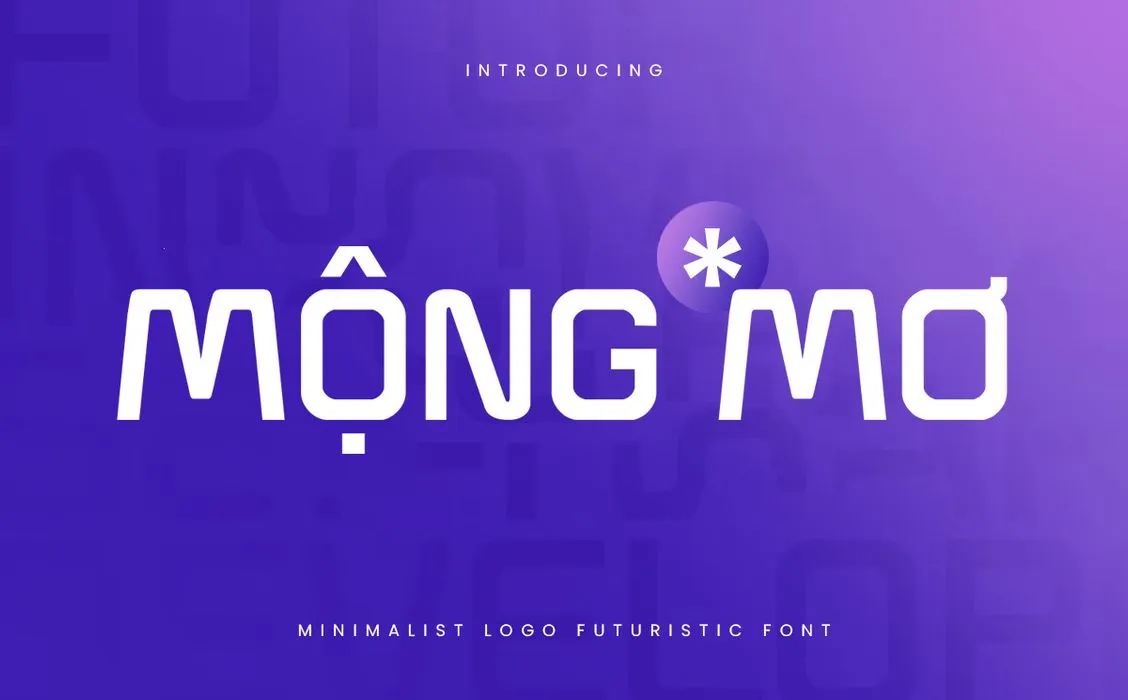
Font TH Wolgen - Tải về
Font TH Glasser - Tải về
Font TH Lugak Sans - Tải về
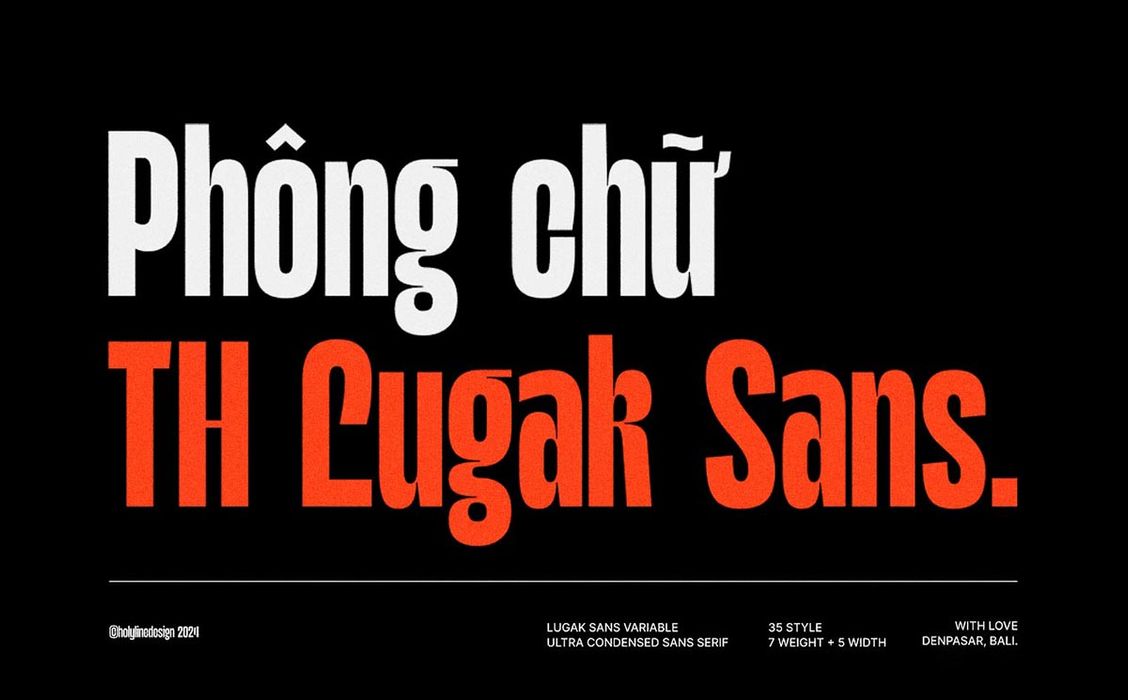
Font TH Wilffer - Tải về
Nhóm này phù hợp cho headline như We are hiring, Tuyển gấp, Join our team, Gia nhập đội ngũ, Hiring now. Tuy nhiên, không nên dùng tất cả nội dung bằng font quá mạnh. Hãy để font hiện đại kéo sự chú ý ở tiêu đề, còn phần mô tả công việc và quyền lợi nên dùng sans-serif rõ.
Với các vị trí quản lý, chuyên gia, cố vấn, giảng viên, nhân sự cấp cao hoặc thương hiệu doanh nghiệp định vị cao cấp, font cần tạo cảm giác chín chắn hơn. Nhóm font sang giúp career page, brochure tuyển dụng, profile công ty và bài đăng LinkedIn nhìn có chiều sâu.
Font TH Luxury 8 - Tải về
Font TH TOP LUXURY - Tải về
Font TH Carline Regular - Tải về
Font TH Selvia Genatu - Tải về
Font TH Wrigskan - Tải về
Nhóm này nên dùng có tiết chế. Nó hợp với tiêu đề chiến dịch, quote văn hóa, tên chương trình quản trị viên tập sự, bài tuyển dụng senior hoặc slide giới thiệu doanh nghiệp. Với nội dung dài như mô tả công việc, yêu cầu và quy trình tuyển dụng, hãy phối cùng sans-serif để giữ độ đọc.
Font chữ tuyển dụng, HR branding tốt phải vừa dễ đọc, vừa truyền được tinh thần nhà tuyển dụng. Job post cần font rõ để ứng viên nắm thông tin nhanh. Employer branding cần font có cá tính để thương hiệu nổi bật. Tài liệu nội bộ cần font ổn định để dùng lâu dài và giữ sự chuyên nghiệp.